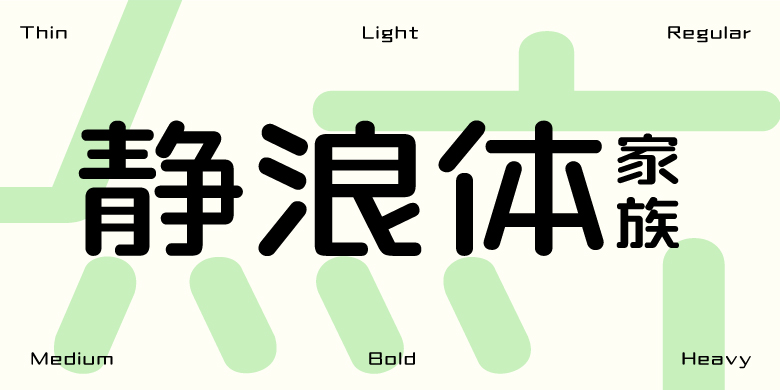
方正静浪体家族
方正静浪体家族,这款字体结构工整、笔画清晰,兼顾美观与易读性,适用于标题、正文、海报、包装、LOGO 等多种场景。字形优雅稳定,风格百搭耐看,适配日常排版与创意设计,让文字呈现更舒适、更具质感。方正静浪体家族一笔一画,皆是细节,以均衡的比例、流畅的线条打造舒适视觉体验,字形端正大气,风格简约现代。无论是商业设计、品牌宣传还是日常排版,都能轻松驾驭,让文字更有格调与力量。方正静浪体家族字体下载。
这款家族字体有六个不同粗细,字形浑厚宽平,笔划没有使用过多复杂修饰使之简约顺滑,给人以平和质朴之感,适用于对领域的宣传使用。